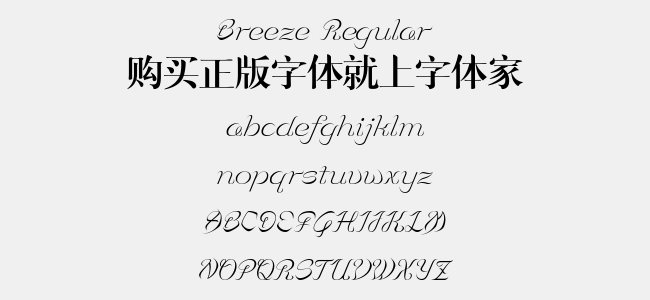
Breeze Regular
字体作者:三极字库
字体名称:Breeze Regular
字体字数:26个英文大小写字母及和阿拉伯数字
字体家族:三极系列
书体类型:英文类
字体公司:三极系列
Breeze Regular
Breeze Regular是一款个性独特的英文字体,非常适合创意类的PS字体,英文广告设计载体上使用,在设计中选择这款字体应用的话,会起到非常理想的效果。此款字体适用于个人学习交流,字体研究以及一些非商业用途的载体中,由三极字库出品,字体家平台整理发布。
Breeze Regular - 大写字母/小写字母/数字